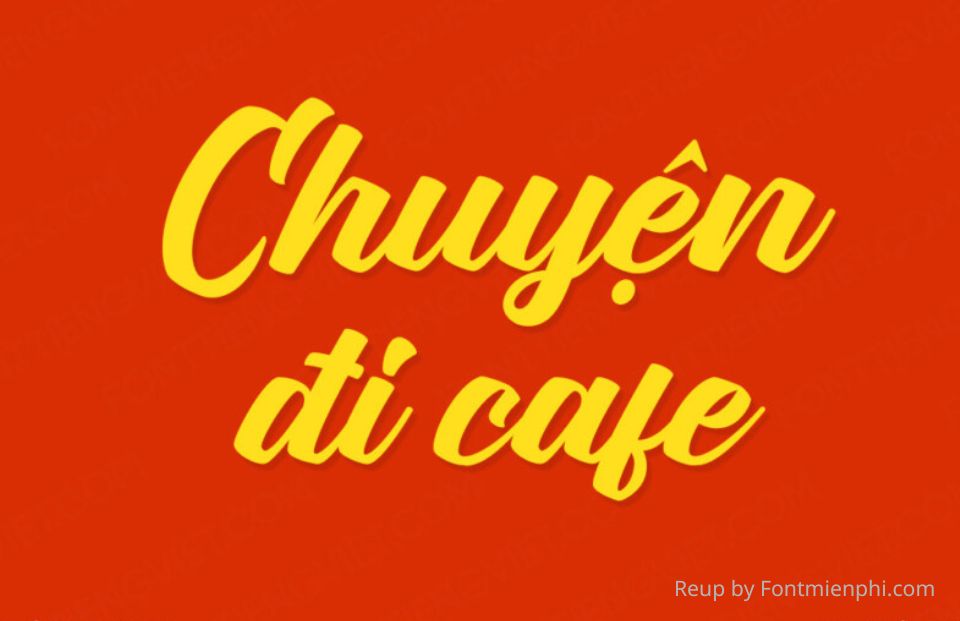
Font Việt hóa 1FTV VIP Hullgaria – Font chữ viết tay cá tính
Font Việt hóa 1FTV VIP Hullgaria là mẫu font script hiện đại, nổi bật với những đường nét viết tay mạnh mẽ kết hợp cùng phong cách retro đầy cá tính. Font sở hữu kiểu chữ đậm, mềm mại, nhiều ký tự thay thế và đường nét trang trí đẹp mắt, phù hợp cho các thiết kế cần tạo điểm nhấn.
Ứng dụng của font Hullgaria
Font 1FTV VIP Hullgaria phù hợp để thiết kế:
• Logo và bộ nhận diện thương hiệu
• Poster, banner và ảnh quảng cáo
• Bao bì sản phẩm, nhãn hàng
• Áo thun, merchandise và biển hiệu
• Tiêu đề video, bài đăng mạng xã hội
• Thiệp mời và các sản phẩm in ấn sáng tạo
Với phong cách trẻ trung, mạnh mẽ nhưng vẫn giữ được nét thủ công tự nhiên, Hullgaria đặc biệt phù hợp với các chủ đề thời trang, thể thao, đồ uống, du lịch và thương hiệu phong cách sống.